近日Brand New网站投票评选出去年品牌升级的一系列榜单,包括最佳和最差排行,下面是给大家整理出10个最佳品牌升级,一起来看一下去年哪些国外品牌的升级最精彩呢。
之前的旧标志简约典雅,已经是很不错了,而新的标识又前进了一大步,图形和文字的大小关系更加得体,使得图形看起来更加优雅庄重;郁郁葱葱的深绿也呈现出更高的品质感。
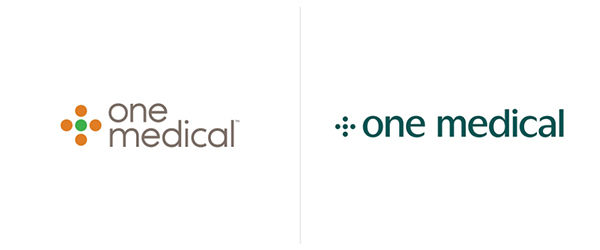
新旧标志对比
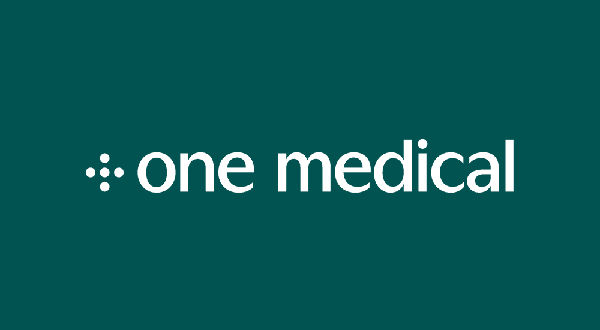
新标志由Moniker设计
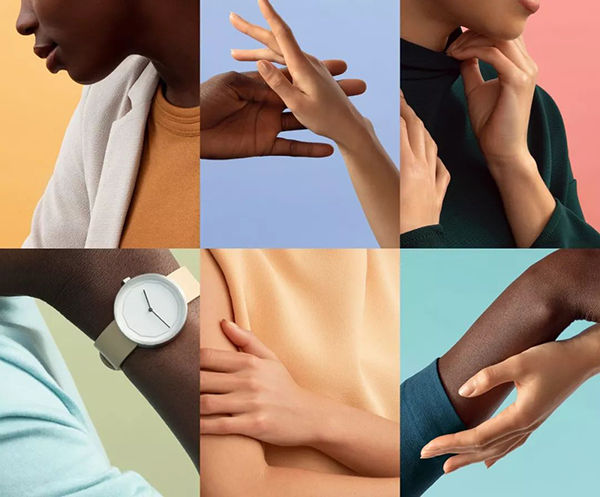
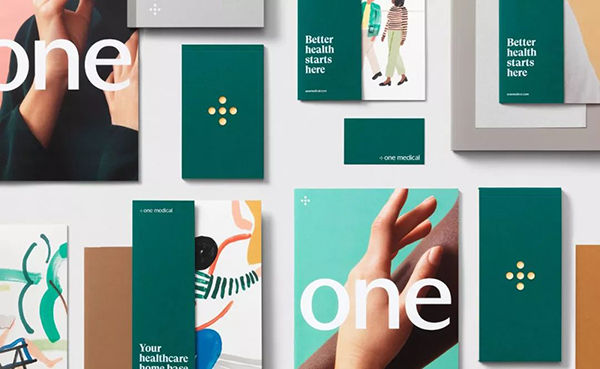
Field Museum成立于1893年,是世界上最大的自然历史博物馆之一,收藏了约3000万件文物和标本。
旧标识相当糟糕,在一条笨拙的线条上依附衬线体,三个单词大小的差异也让人觉得过于随便。而新的标志大胆让人印象深刻,两个正方形:小方块代表展出的博物馆藏品的一小部分,而标识本身的方形,代表了博物馆的整个大型收藏品;蓝色体现了乐观和不断努力发现更美好世界的解决方案。
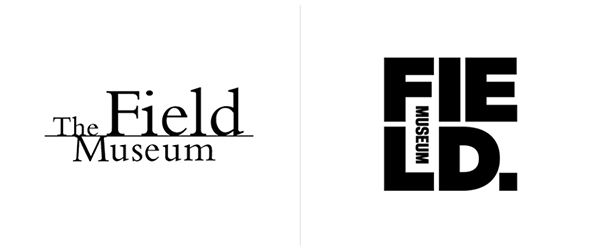
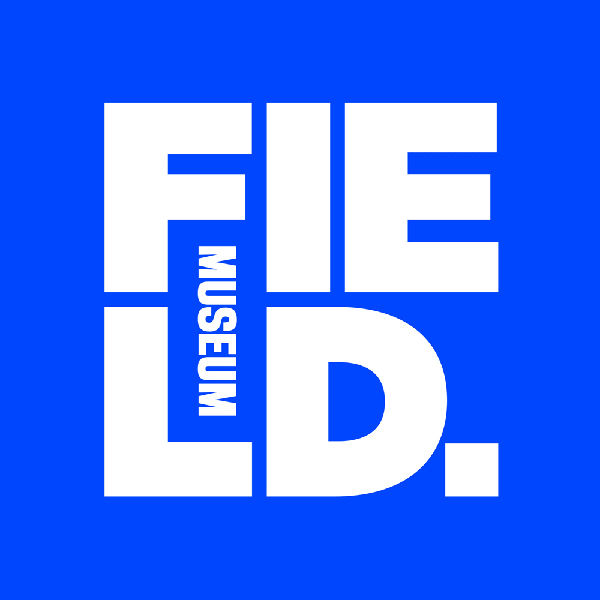
新标志由芝加哥Leo Burnett设计
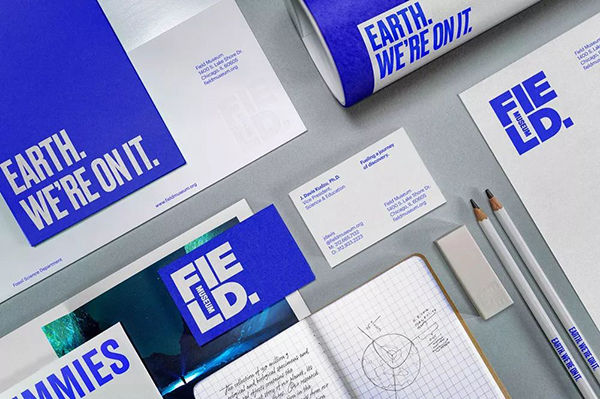
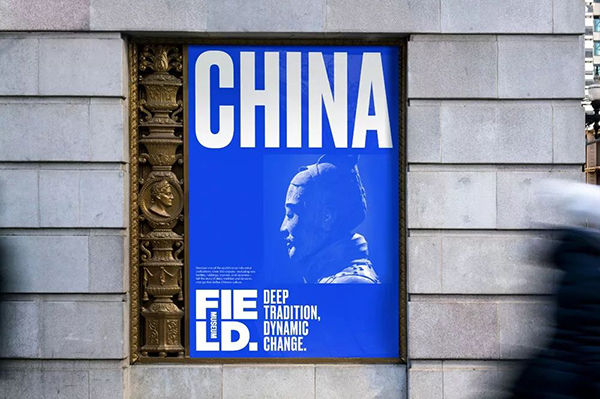
旧的标识是直截了当的对于狗和猫的直接描述,并放到一个不错的排版圆圈之内;相比其他相关领域的标识要好得多,但仍然容易让人遗忘。
相比之下,新的标识打破这一细分市场的常用手法,采用非常迷人的狗和猫的水彩画,黑色的耳朵、胡须、鼻子更是奇思妙想的一笔,大写文字表达出意思严肃,整体可爱又与众不同。
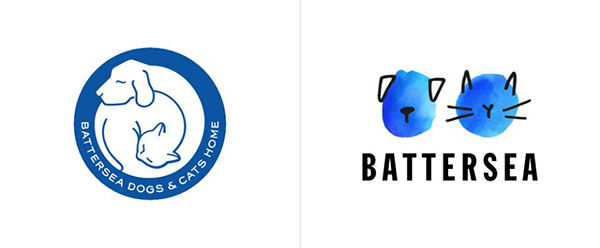
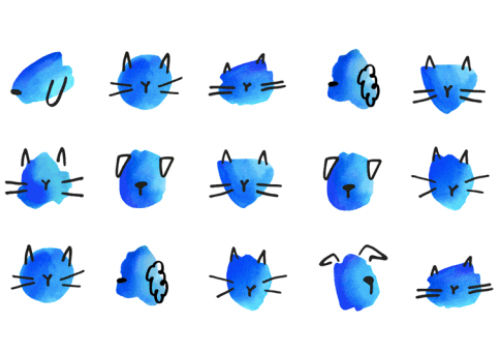
英国伦敦pentagram设计
旧徽标不差,但它也不够好。看起来像是老派的广告业代表,让人感受不到新鲜和现代。新的标识虽然基于90年代的旧标识设计的,但却充满了活力和现代感,字母“g”的变化非常独特,整体标识并且有着良好的应用性,可以垂直甚至堆叠。
新标志
之前的标识采用比较偏向手写感的形式,但它还是过于坚硬,看起来更像是一些标题涂鸦,而不是美味诱人的巧克力标识。
新的标识保留了原始的基本结构,但是线条采用干净利落的等线,感觉更现代,字母之间的关联和流畅性也做的更好了。
新标志和包装由旧金山的Simon Blockley设计
旧包装和新包装
新包装
Dunkin'Donuts成立于1950年,是世界上最大的烘焙食品和咖啡连锁店,在全球拥有超过11,300家餐厅。今年,该公司宣布将更名为Dunkin',放弃了Donuts部分。
新标识保留了1973年推出的熟悉的粉红色和橙色以及标志性的字体,与之前保持一致。
Freddie图标一直是品牌的主要标志,这一次更新对它进行了简化,其形状和细节进行了调整,以确保它在任何尺寸下看起来都很棒。并且开发了一套与Freddie图标协调一致的字标,使两者看起来更加均衡。
颜色选取上,在某种程度上因为香蕉是黄色的,猴子吃香蕉,这种深黄色感觉既有趣又精致,尤其是搭配黑色时。
算是比较温和的更新,但是你能看到的效果是显著的。旧标圆润的端点看起来亲切友好,而新标看起来更加扁平散发出严肃、规范的气质,这很有趣。平头的端点会使得“SS”看起来更易识别,又能够保持之前的抽象性。
另外,新的字体真的是非常棒,变得更有细节,也更加偏向商业、主流,同时和图形的粗细关系也变的更协调。
图形由NY-based DIA设计
古老的标识以印章的形式展现,描绘了希腊神话中的历史缪斯克里奥,这没有什么不好,但问题是这不是一个很实用的标识。
新的标识则灵活得多,并且建立了一个更易记忆、识别和更高关联性的图形,字体的选用也保留了旧标识的学术感,也会有更多的现代感。
新标识
汉莎航空成立于1955年,是世界领先的航空公司之一,总部位于德国。
其原始图形已经使用了100年,设计于1918年。而新的图形从本质上讲,与1962年以来保持一致,只是在电脑软件的辅助下已被重新绘制以表现更好。最大的变化是外环变细,尽管变化微妙但却让它感觉更加优雅;机翼的羽毛略微打开,使图标更容易阅读。虽然变化很小,但每个变化都提供了更强大的性能改进。
多年来图形的更迭
图形变化前后
字体的前后变化